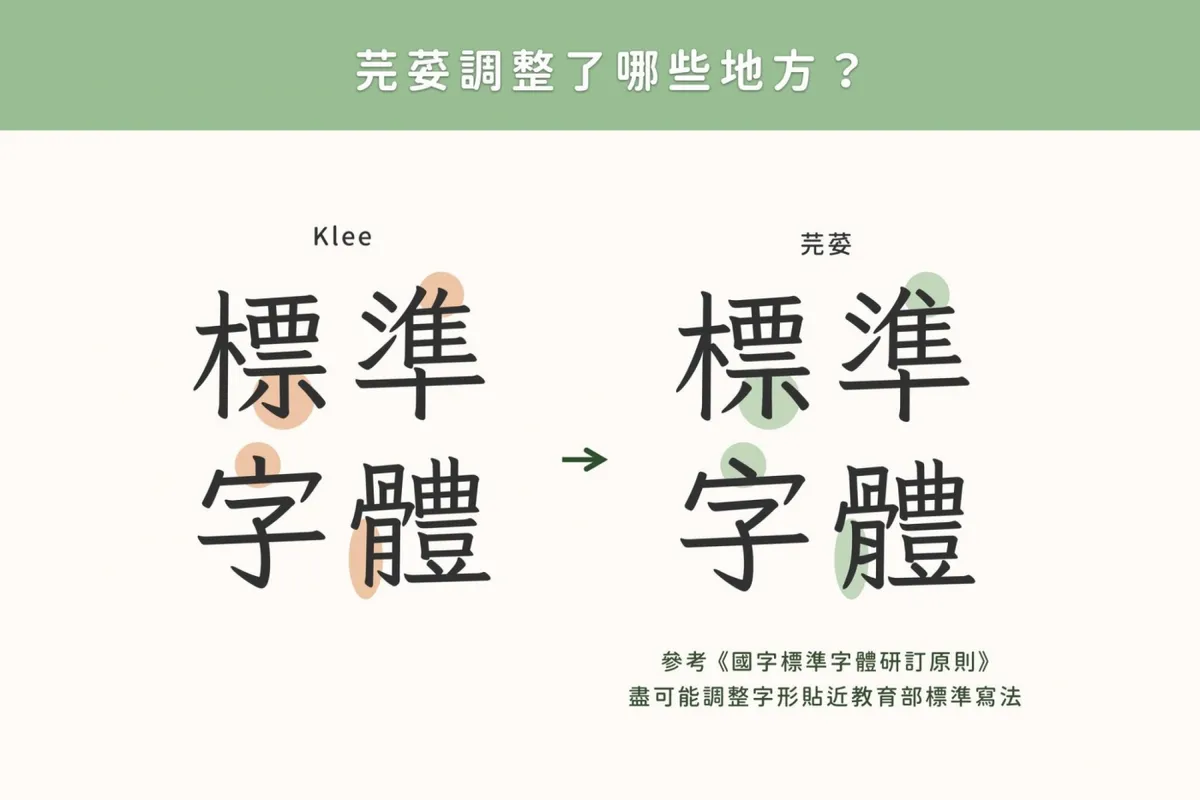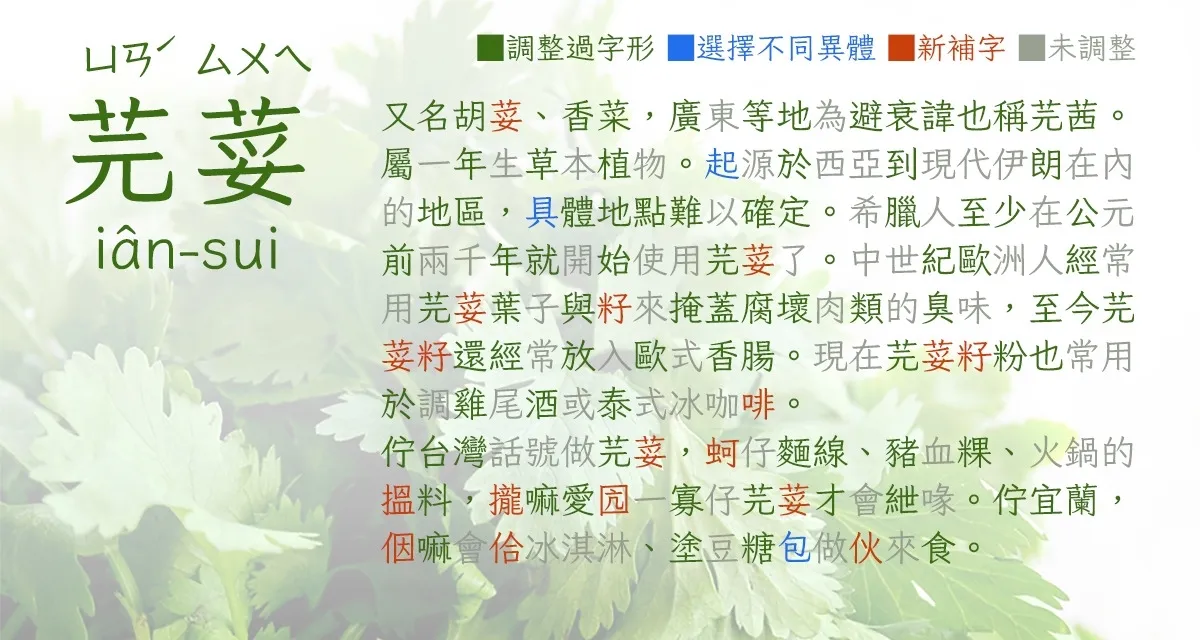
芫荽
第一套為台灣教育使用所改造的繁體硬筆楷書字型「芫荽」開放免費下載,該字體由字嗨發起人But Ko基於Fontworks Klee One改作,保有原本的楷體、仿宋筆調,外型溫潤且線條易讀,但改善了缺字情況、排版上的不便,且盡可能調整字形貼近教育部標準字體,補充台客語用字,打造更貼近台灣需求,並適合學齡教育使用的新字型「芫荽」。
Fontworks 的 Klee(クレー)字型原本內建於 macOS,因其兼具楷體與仿宋的筆調、高易讀性與溫暖外形,廣受中文使用者喜好;然而畢竟是日文字型,雖然字數不少,但排中文時仍有一定程度缺字,一直是可惜之處,為了解決上述的問題,新字型「芫荽」誕生了,它是由字嗨發起人But Ko基於 Fontworks Klee One所改作,也是台灣第一套開源的硬筆楷書字型。
But Ko以Klee One字型為基礎,改善繁體中文使用上缺字、與原日文字體寫法不同的問題,像是將全形標點符號由偏左下調至置中,嘗試盡可能調整字形貼近教育部標準字體,補充台客語用字,貼近台灣需求,並適合學齡教育使用,如童書、國字習作等,也讓大家在設計教科書、學習單、繪本教材等不同學習媒材時,多了一款硬筆楷書的選擇。